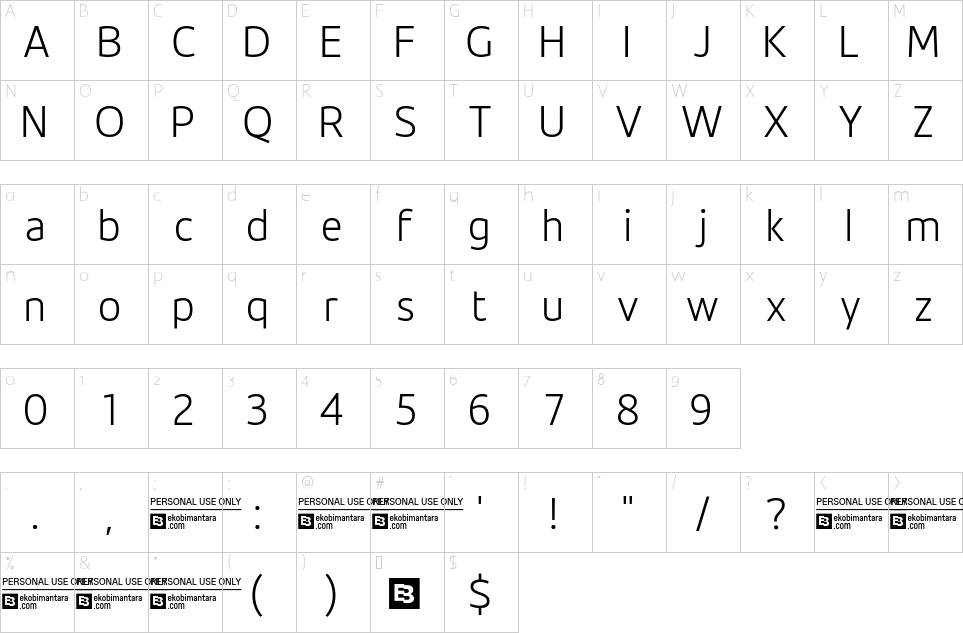
A fonte Digiva é uma escolha ótima para designers que buscam adicionar um toque diferenciado às suas criações digitais, especialmente no ambiente brasileiro vibrante e variado. Desenhada por Eko Bimantara, ela oferece uma fidelidade impressionante ao estilo dos textos sem comprometer a facilidade de uso em ambientes Windows e Mac. Apesar de não possuir detalhes específicos sobre suas características gráficas, Digiva promete ser uma opção versátil para diferentes usos. Suas linhas leves e elegantes tornam-a ideal para aplicações como sites pessoais ou blogs, logotipos e mensagens digitais onde o foco deve estar no texto. Com mais de 90 downloads ao longo dos meses, a Digiva já se destacou em comunidades de designers online. Este fato é uma indicação clara da sua relevância e qualidade. Caso você esteja procurando por fontes gratuitas para seus projetos digitais, Digiva pode ser uma escolha convincente.